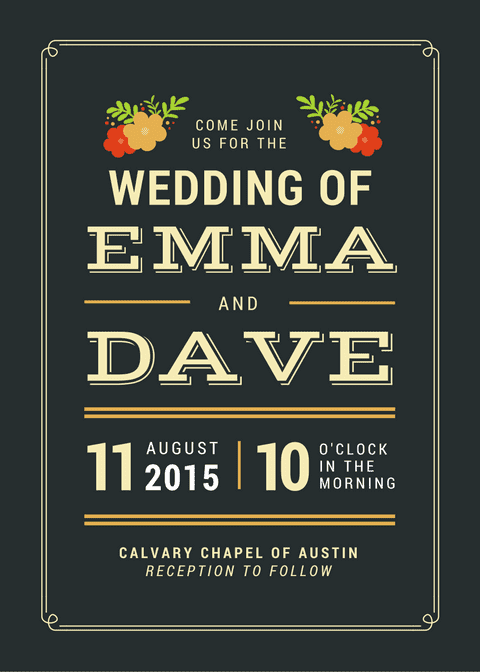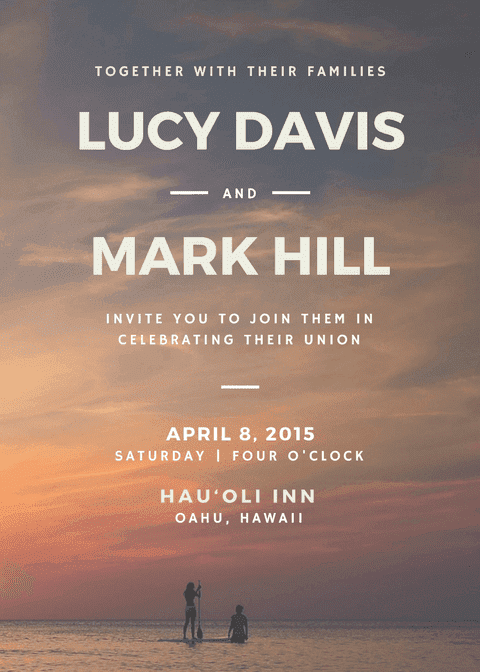
Selain menentukan tanggal, undangan, place card dan hal lainnya, ada banyak teks yang digunakan dalam pernikahan.
Kami tahu akan sangat sulit untuk merencanakan semua detil kecil pernikahan. Oleh karena itu kami ingin membantu Anda menghindari stres untuk urusan yang terkait dengan font. Ada banyak font gratis di luar sana tetapi menyaring dan memilah-milahnya bisa sangat memakan waktu.
Apakah Anda akan mencari tulisan yang rumit, bersih, tampilan modern, atau gaya tulisan tangan, Anda pasti akan menemukan pasangan font yang cocok di surga tipografi hanya untuk pernikahan Anda. Dan jika Anda membaca ini bersama artikel font utama kami, Anda akan menguasai seni menggabungkan font dalam waktu singkat.
Ini adalah kombinasi undangan pernikahan klasik, font kursif yang dipasangkan dengan sans serif. Untuk font kursif, Great Vibes adalah salah satu font yang paling mudah dibaca. Kemiringannya halus, tebal yagn sedang, dan tinggi x-nya memberikan aksesibilitas yang hebat sebagai bentuk tulisan yang elegan. Montserrat mengimbangi fitur kepala yang bulat dengan garis lurus yang seragam.
Dengan bentuk tulisan yang miring, Anda bisa sedikit lagi memiringkan sudutnya. Ini akan menambah daya tarik pada desain Anda tanpa mengurangi keterbacaan teks Anda.
Font serif memiliki daya yang tarik yang abadi begitu juga undangan pernikahan Anda jika Anda memilih pasangan font ini. Tampilan Playfair adalah font serif tipe klasik dengan transisi halus antara garis tebal dan tipis. Yang ditonjolkan pada desain ini adalah Montserrat Light, linieritasnya sesuai dengan struktur tegak dari Playfair tanpa terlalu mendominasinya.
Tulisan yang miring memberikan nuansa pada pasangan font utama dan berfungsi sebagai sub judul tanpa beralih fungsi sebagai font ketiga.
Pasangan font ini seperti kebalikan dari kombinasi kami sebelumnya. Josefina, font sans serif, digunakan sebagai judul utama sementara font serif sebagai font pendukung. Kombinasi ini sesuai karena ketebalan Josefina tidak kalah dari Times New Roman sehingga membuat hirarki yang harmonis.
Bentuk font yang ramping juga sesuai dengan desainnya. Tepi tajam dari garis pembatas mewakili bentuk bentuk siku Josefina yang tajam. Di sisi lain, tampilan dasar geometrisnya tampak kontras dengan baik dengan ilustrasi bebas di garis pembatas.
Kami melihat Montserrat banyak dipakai sebagai font pendukung tapi Montserrat sama baiknya saat menjadi font utama. Pada kombinasi ini, Montserrat tampil sebagai font yang tebal begitu juga font pasangannya, Hammersmith One. Font lain biasanya akan didominasi atau bersaing dalam hierarki, tapi Hammersmith One memiliki ketebalan yang tepat sebagai font pasangan. Keduanya adalah font kuat yang menonjol dari latar belakang fotografinya.
Bodoni adalah font modern, ini artinya ada kontras tinggi antara goresan tebal dan tipis, dan serif benar-benar datar. Josefin Sans di sisi lain adalah font yang terinspirasi vintage geometrik. Keduanya adalah pasangan kontemporer vintage yang tampil sempurna dalam desain yang sederhana.
Ini adalah contoh lain kombinasi dari playfair Display dan Montserrat. Tidak dalam huruf kapital seperti yang pertama (pasangan font #2), Playfair di sini hadir dalam bentuk kalimat. Tampilan tulisan yang tebal menekankan bentuk tulisan Playfair Display yang cantik, yang digunakan sebagai judul utama dari desain minimalis ini. Montserrat digunakan untuk detil pernikahan dalam gaya biasanya dan fungsinya sebagai sub judul.
Pasangan ini membuktikan bahwa Anda tidak perlu susah-susah mencari pasangan yang sempurna, karena mereka mungkin saja berada didekat font lain dalam menu font. Josefin Sans dan Josefin Slab adalah font yang sejenis namun dengan rasio ukuran, jarak, dan bentuk teks yang tepat kedua tipe ini bisa saling menuansa satu sama lain seolah-olah bukan dari keluarga font yang sama.
Jika Anda mencari tampilan klasik untuk undangan pernikahan Anda, tidak perlu jauh-jauh. Pinyon Script adalah font yang akan Anda cari untuk pesta pernikahan kerajaan. Pasangkan dengan jenis serif seperti Forum lalu beri warna emas maka Anda akan mendapatkan undangan pernikahan klasik yang cocok untuk pernikahan tradisional.
Vidaloka juga adalah tipe serif modern seperti bodoni, hanya sedikit lebih tebal dan lebih lebar dari yang terakhir. Desain dengan elemen ilustrasi yang berani seperti gambar dua wanita dalam contoh di atas harus didukung dengan font judul yang kuat, jangan sampai hilang dalam undangan. Ketipisan dan kesederhanaan dari font pelengkap Lato melembutkan blok warna yang diciptakan oleh elemen utamanya.
Font sans serif yang indah buatan KAIWA ini mudah dibaca, sederhana dan halus yang menjadikan font ini adalah pilihan sempurna untuk teks program pernikahan atau cetakan kecil di undangan.
Meski font ini lebih tebal dari Mightype, font tulisan tangan yang sangat manis buatan Mats-Peter Forss dan Emily Spadoni ini mempesona dengan sendirinya. Namun buah cherry di atas yang digunakan sebagai hiasan gantungan tambahan akan membawa desain Anda ke tingkat berikutnya.